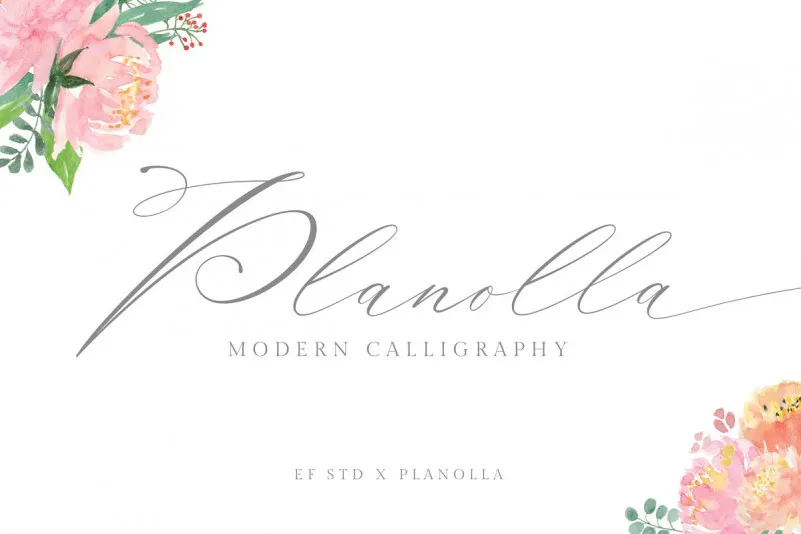
Planolla Calligraphy Font
Esta é uma nova família de fontes calligrafia modernas que traz ao designer algo único e versátil para seus projetos digitais. Introduzindo a Planolla Font, esta é uma combinação inovadora entre o estilo da calligrafia e a arte do pincelado, criada em parceria com o talentoso artista Planolla. Esta fonte de script moderna oferece um look elegante e sofisticado que pode ser usada para adicionar um toque pessoal aos seus designs. É perfeitamente adequada para aplicar em cartões devidas, identidades de marca, convites de casamento, logotipos e muito mais. A Planolla Font apresenta a essência da calligrafia moderna com uma dose de beleza artesanal que faz dela uma escolha ideal para qualquer projeto visual que deseje agregar um toque especial.